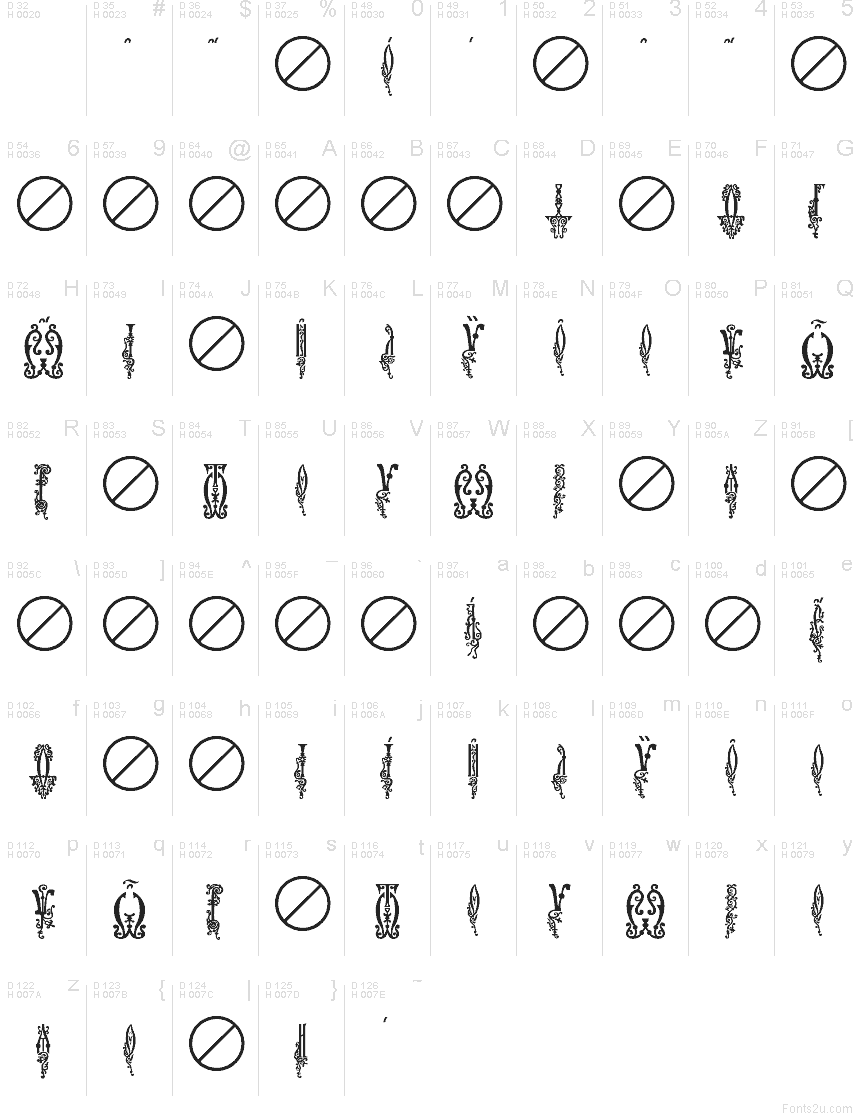
Písmo Bukvica UCS, které vytvořil Constantin I. Spektorov, je bezplatný umělecký dingbatový font plný zdobných, vertikálně komponovaných symbolů. Zrcadlené spirály a kapky se zde setkávají s tvary připomínajícími čepele i formálními monogramy, vykreslenými jako ostré a propracované siluety.
V rozhraních fantasy her i na plakátech experimentální hudby nabízejí tyto symboly v nejrůznějších typech médií stejnou rituální, heraldickou atmosféru. Hodí se také na knižní obálky a tematický reklamní sortiment. Vybraný znak může spíše než běžný text posloužit jako erb frakce, oddělovač kapitol nebo dekorativní emblém.
This font is disigned for the initial letter of a book or a capital (NOT for typing the whole words or sentences). Such font for initial letters was used in the Moscow "Pechatny Dvor" (Printing Yard) in the 1st half of the 17th century. Special thanks to Theodosy (Roman Travin) and Vladislav Dorosh.